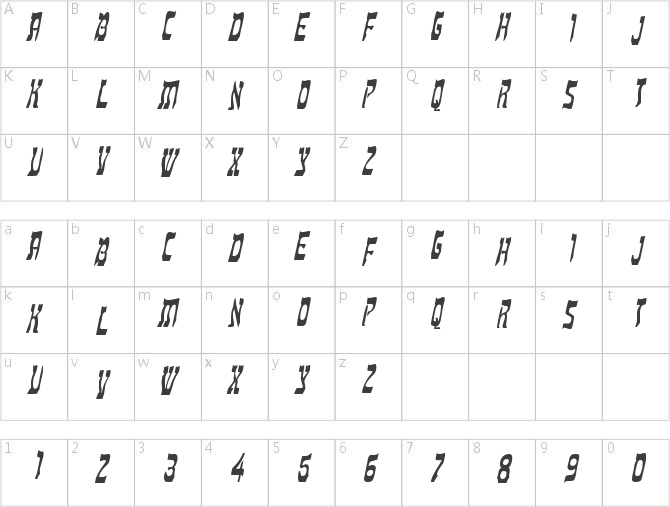
Kosher-Thin-Italic 詳情頁
字體名稱: Kosher-
Kosher-Thin-Italic
Kosher-Thin-Italic介紹
Kosher-Thin-Italic字體字庫是一款讓人賞心悅目、百看不厭的英文字體,適合各類廣告和產品包裝設計應用,字體大小0.07MB,格式為ttf字體,上傳用戶是黃肖,作者/版權方為未知